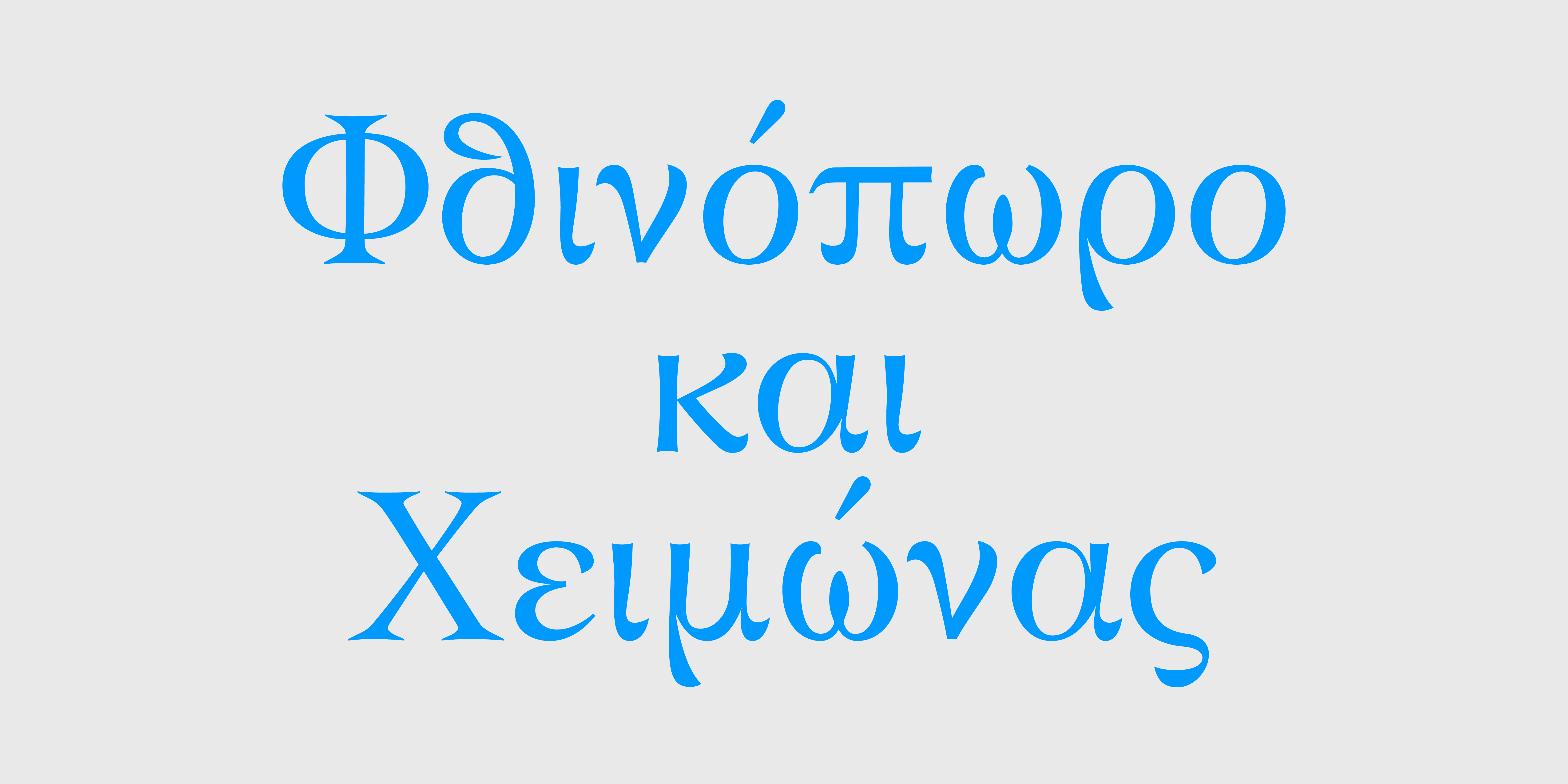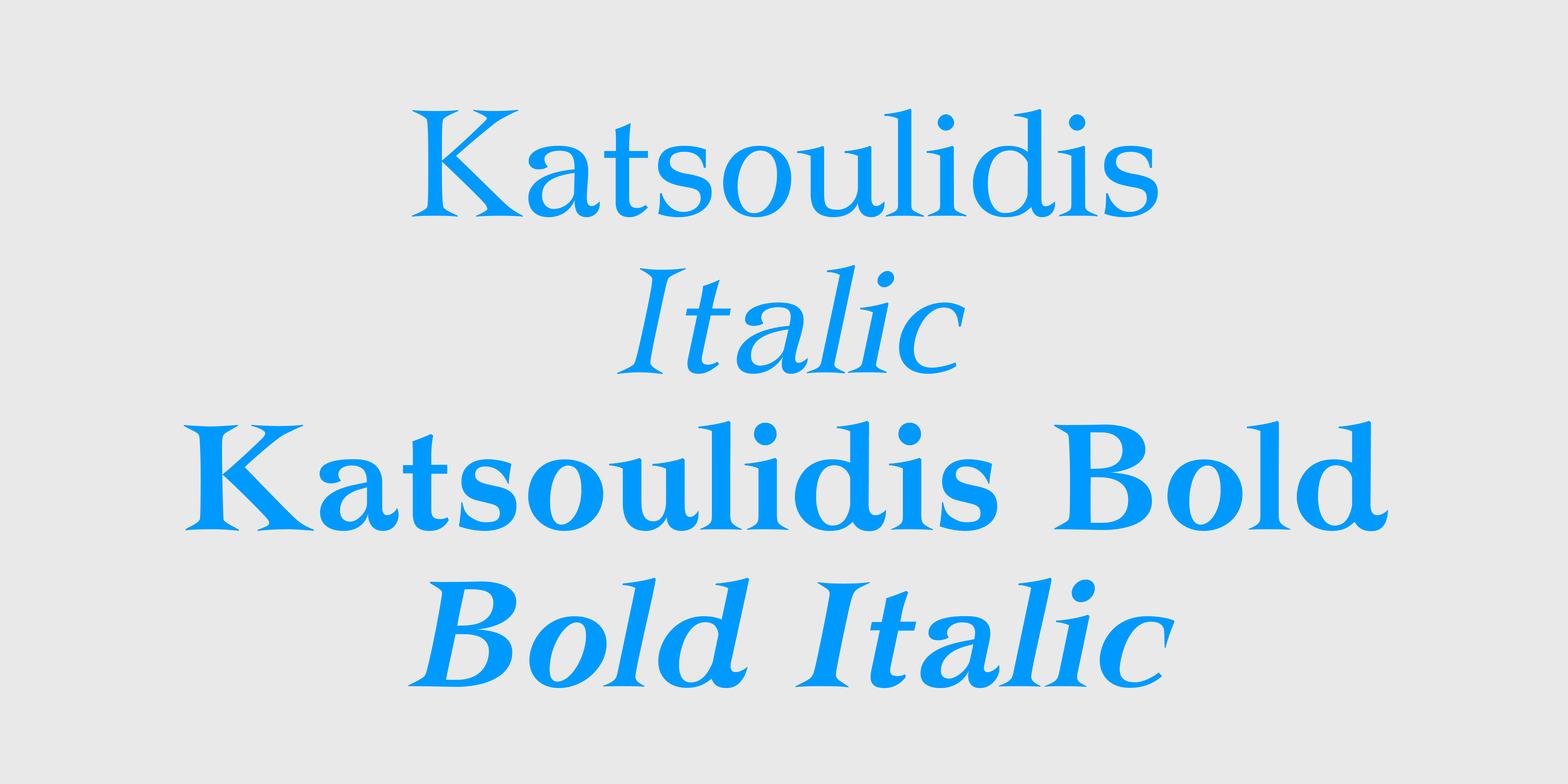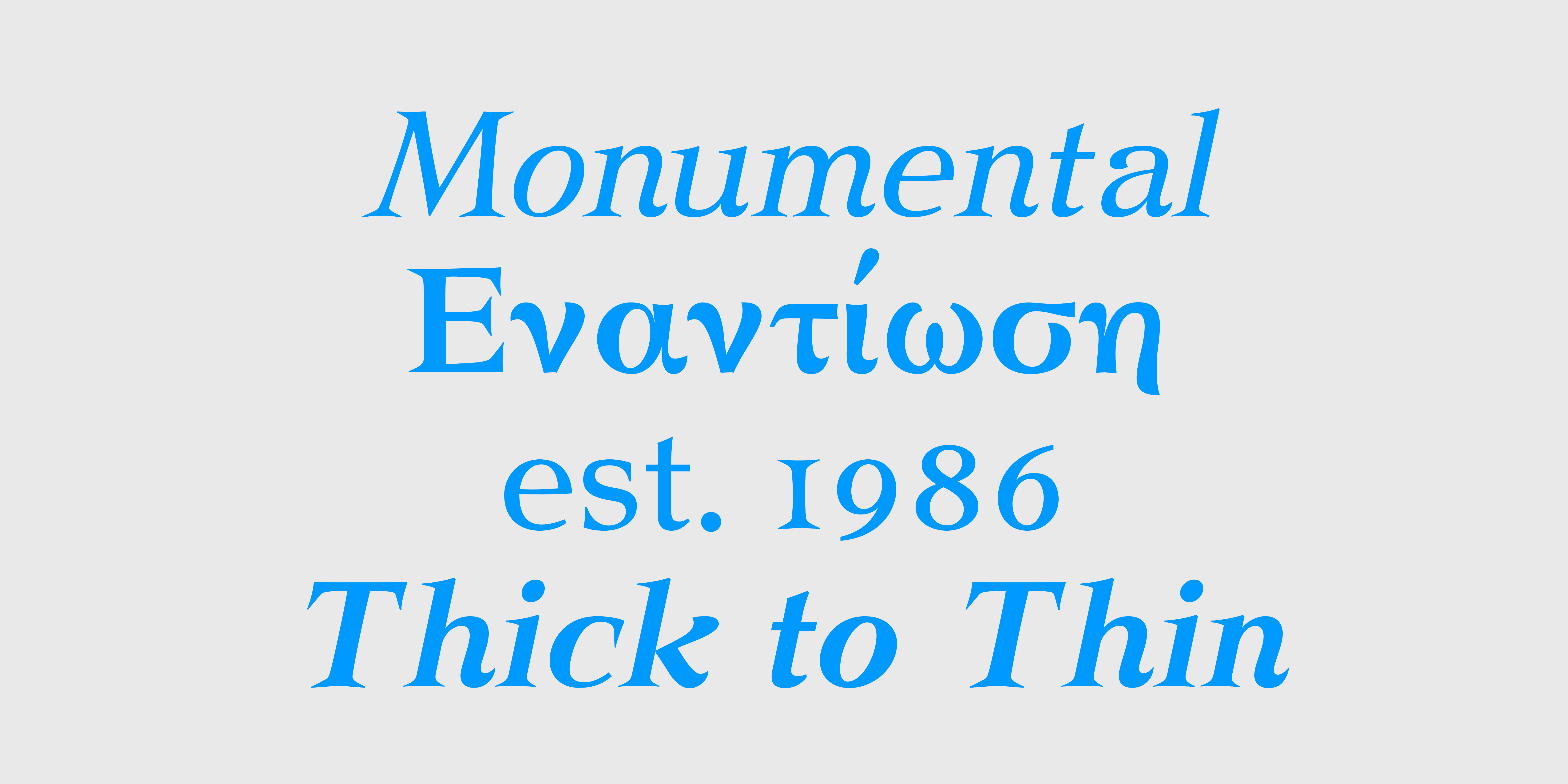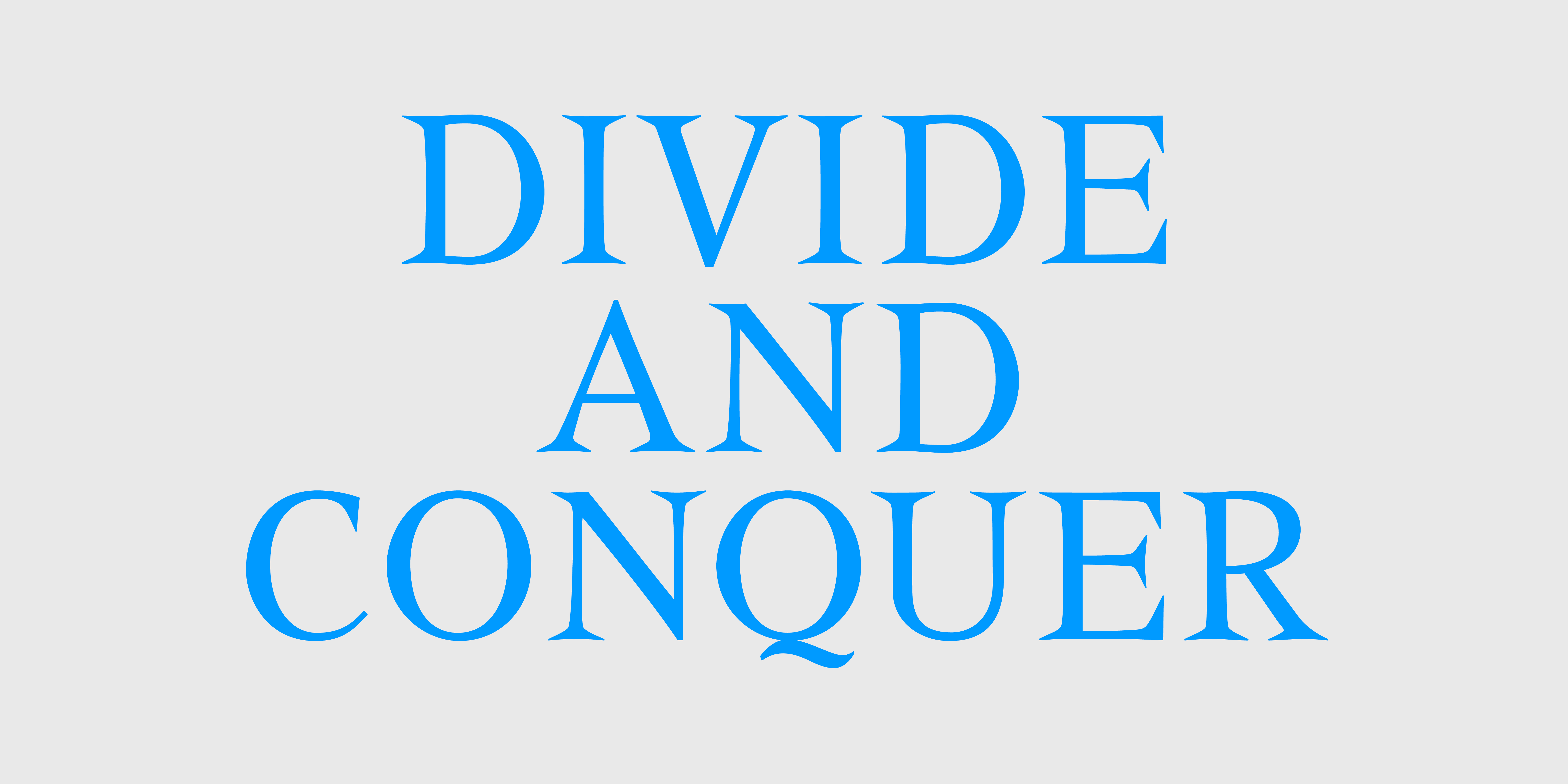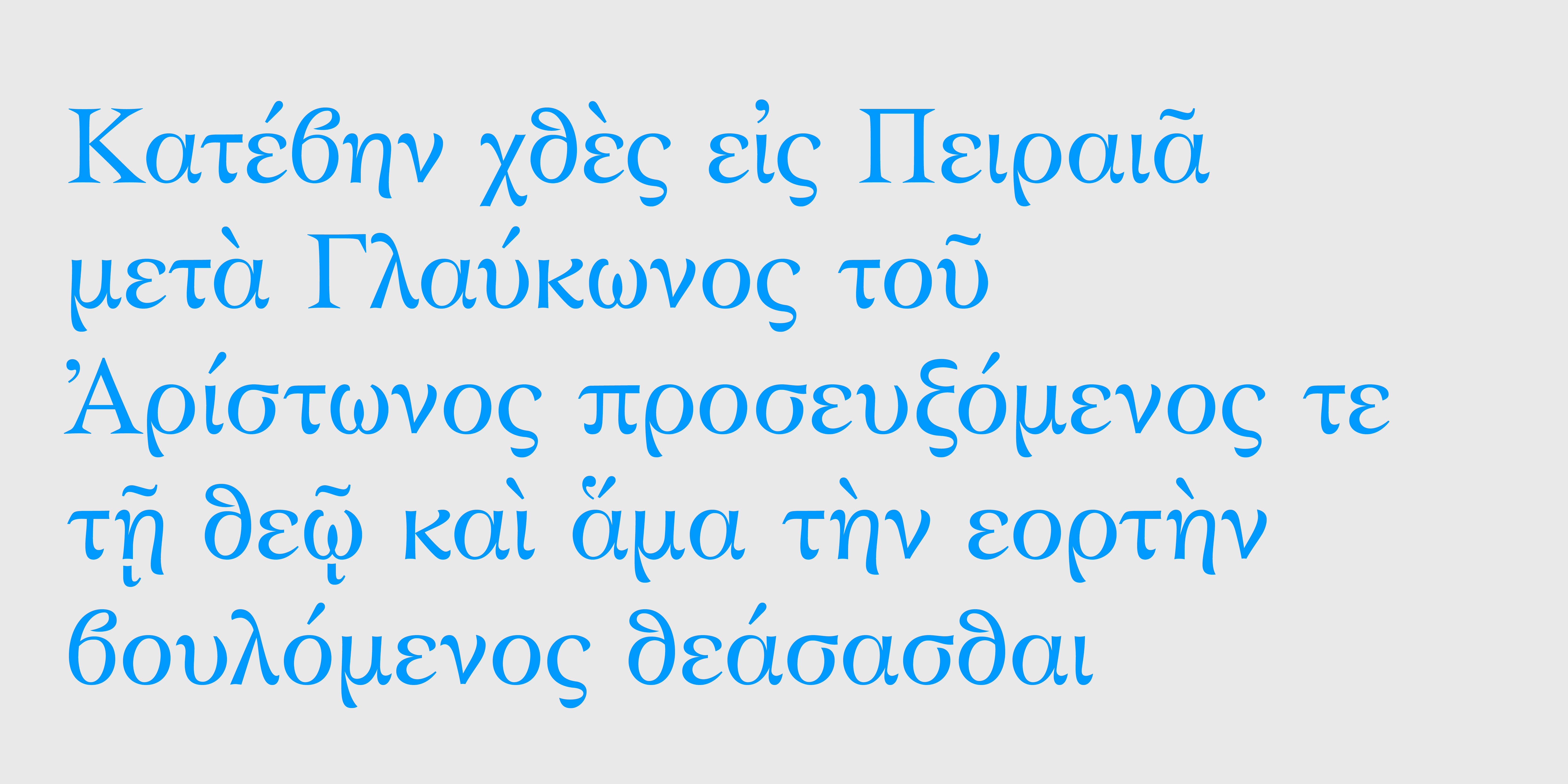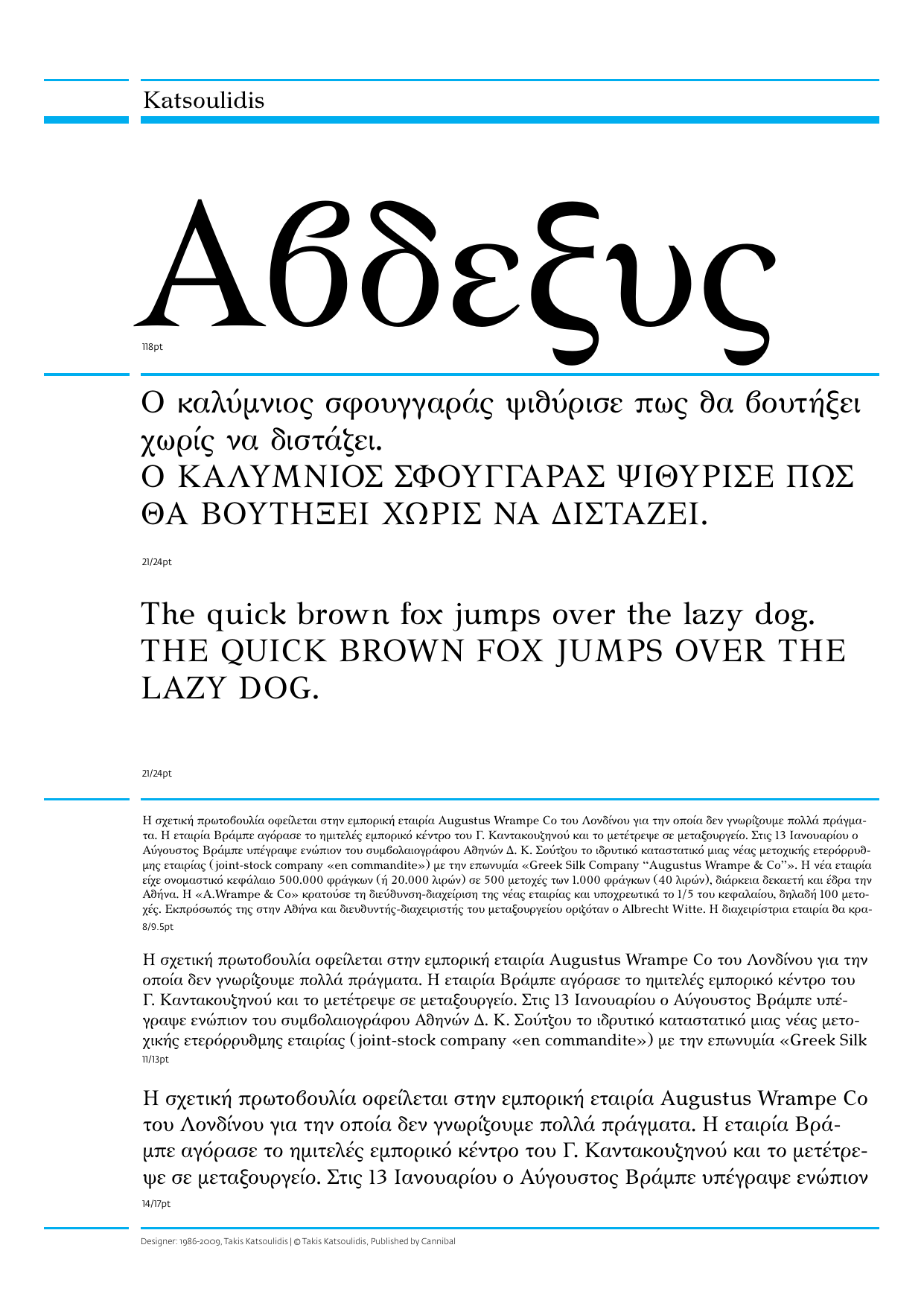
Katsoulidis
Πρόκειται για εξέλιξη των Ελζεβίρ όπου κυριαρχεί η καμπύλη σε βάρος της ευθείας. Ο οφθαλμός των πεζών στοιχείων έχει μεγαλώσει σημαντικά κι αυτό κάνει τα γράμματα περισσότερο ευανάγνωστα από μικρές στιγμές. Η οικογένεια Κατσουλίδης παρουσιάστηκε μαζί με την οικογένεια Απολλώνια έπειτα από μελέτη που άρχισε το 1986, στα πλαίσια ερευνητικών προγραμμάτων των ΤΕΙ, η οποία μαζί με το σχεδιασμό διήρκεσε μέχρι το 1989. Η νέα έκδοση που κυκλοφορεί από το 2010 είναι επανασχεδιασμένη ενώ έχουν προστεθεί νέα σύμβολα και χαρακτήρες ώστε να υποστηρίζονται πλήρως το Western και Central European Character Set. Στη νέα έκδοση περιλαμβάνονται επίσης 4 είδη αρίθμησης (Lining, Tabular Lining, Old Style, Tabular Old Style). (Πληροφορίες από το βιβλίο του Τάκη Κατσουλίδη, «Το σχέδιο του γράμματος»).
Oldstyle Figures
Standard Ligatures
Μία Eξέλιξη των Ελζεβίρ
Aφετηρία της ελληνικής τυπογραφίας
Χαραγμένα στη Μνήμη
Από το σχέδιο του γράμματος